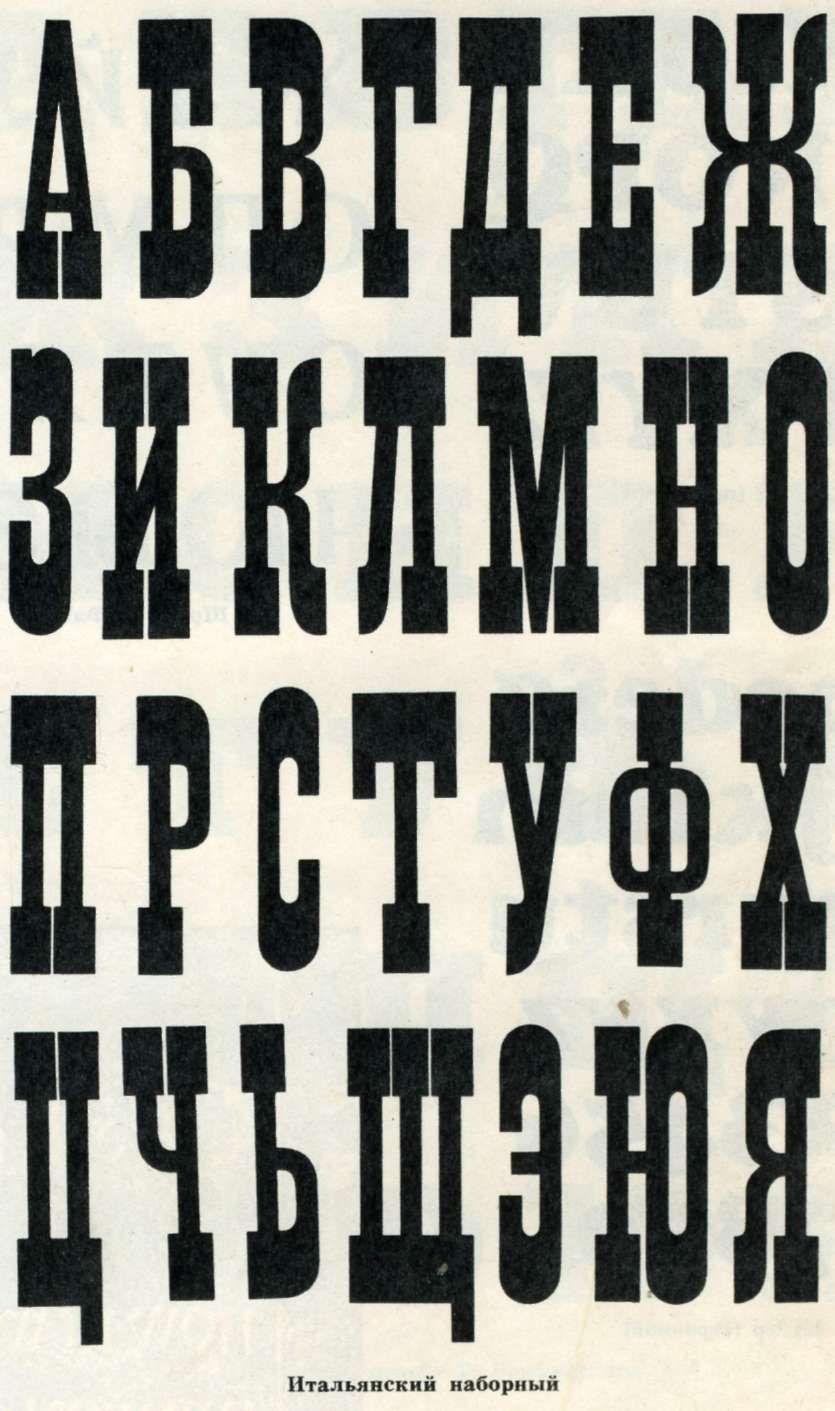
за что ненавидят Comic Sans, Lobster и Papyrus / Skillbox Media
Дизайн не может нравиться всем. Его восприятие во многом субъективно — хороший он или плохой, обычно определяют по тому, нравится ли целевой аудитории. Но в профессиональной среде есть свои табу: например, несколько шрифтов, которые признаны некачественными или избитыми — и преданы анафеме. Хотя даже их кое-где используют!
Рассказываем истории «плохих» гарнитур: за что они попали в немилость и где их всё ещё можно увидеть.
Если вы интересуетесь дизайном, то, скорее всего, где-то видели этот шрифт:
Изображение: Hip FontsЭту гарнитуру в 1982 году разработал дизайнер Крис Костелло (Chris Costello): ему было 23 года, и это был его первый шрифт, созданный в качестве личного проекта. Однако спустя два года права на него купила британская шрифтовая студия, и Papyrus вышел в свет. Кириллическая версия появилась уже в начале нулевых — её сделали другие дизайнеры.
После выхода шрифт стал довольно популярным, его использовали в разных сферах. Но если сейчас загуглить это название, на первой же странице поисковой выдачи половина ссылок будет вести на статьи и дискуссии о том, что использовать Papyrus — моветон. У этого есть две основные причины.
Во-первых, слава декоративных шрифтов никогда не длится долго — люди от них устают. Если, например, Helvetica или Times New Roman — нейтральные наборные гарнитуры, которые так же нейтрально смотрятся спустя десятилетия, шрифты с необычной формой букв и текстурами подчинены моде. Поскольку Papyrus в своё время слишком часто использовали, он теперь вызывает ощущение дежавю.
Во-вторых, Papyrus часто ругают за то, что он недостаточно аутентичный. Название отсылает к древности, но по форме букв трудно понять, письменность какого этноса тут имитируют. Papyrus, в зависимости от настроения, можно счесть египетским, греческим, месопотамским или ещё каким-нибудь.
А текстура по контурам букв смотрится не слишком правдоподобно — видно, что все эти неровности просто нарисованы в векторном редакторе. Из-за этого Papyrus приобрёл флёр мультяшности.
Несмотря на то что этот шрифт активно ругают дизайнеры, иногда его до сих пор используют — даже во всемирно известных проектах. Самый громкий пример — заставка фильма «Аватар»:
Изображение: IMP AwardsКак видите, в названии первой части использовали именно Papyrus — с незначительными изменениями деталей, которые выполнили вручную. Во второй части «Аватара» от этого шрифта уже отказались и выбрали другой, совершенно непохожий.
Шрифты-алфавиты для рекламных и декоративно-оформительских работ 4
Снарский О. В.
С53 Шрифты-алфавиты для рекламных и декоративно¬
оформительских работ — К.: Реклама, 1979.— 152 с., ил.
В предлагаемом издании приводятся образцы рекламных и декоративных рисо¬
ванных шрифтов, переработки и переложения на основу русского алфавита совре¬
менных латинских гарнитур, а также армянского, грузинского и других шрифтов.
Альбом поможет художникам-оформителям и специалистам рекламы в выборе
соответствующего шрифта, профессиональном его выполнении и повышении общей
шрифтовой культуры.
ОТ АВТОРА
художественном оформлении экспозиций
музеев и выставок, мемориалов, световой
печатных изданий шрифту принадлежит видное
место. Формой, цветом, характером букв он
привлекает внимание, вызывает определенное
отношение к содержанию. Вот почему в рекламных
и декоративно-оформительских работах существенное
значение приобретает изобразительное решение текста:
рисунок, образ, ритмика, стиль, цвет и, самое главное,
четкость и удобочитаемость.
Шрифт не только помогает донести смысл текста, но
также передает и настроение, заложенное в нем, имеет
национальный колорит и т. п. Разные по форме и стилю
шрифты вызывают различные исторические ассоциации:
вспомним древнерусский устав, полуустав, вязь, русский
гражданский шрифт.
Шрифтам посвящены многочисленные издания. В них